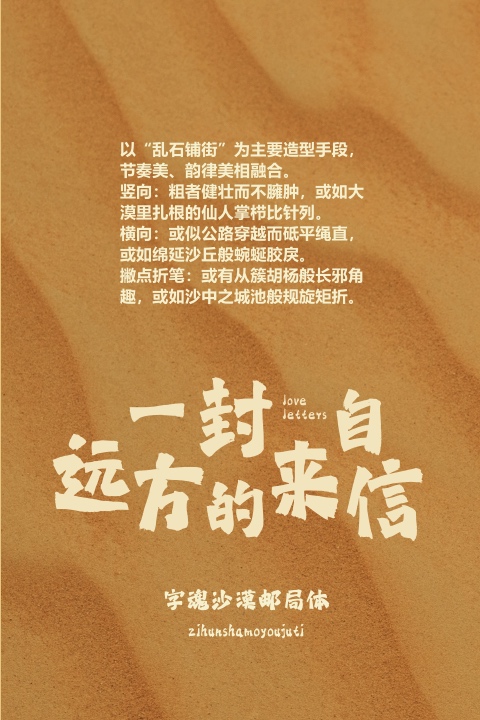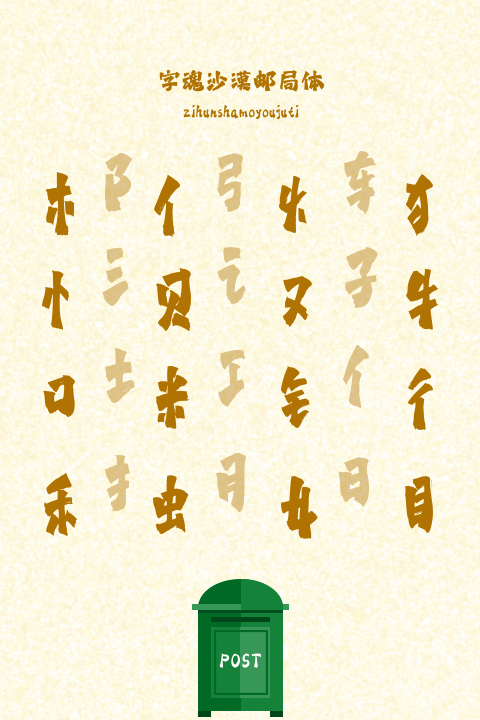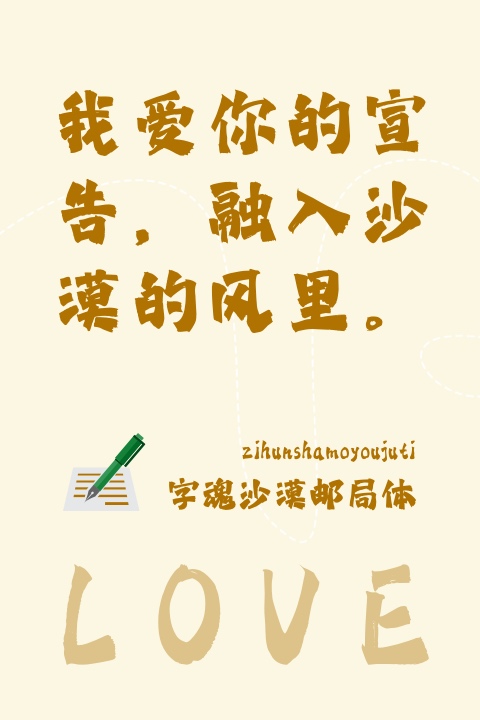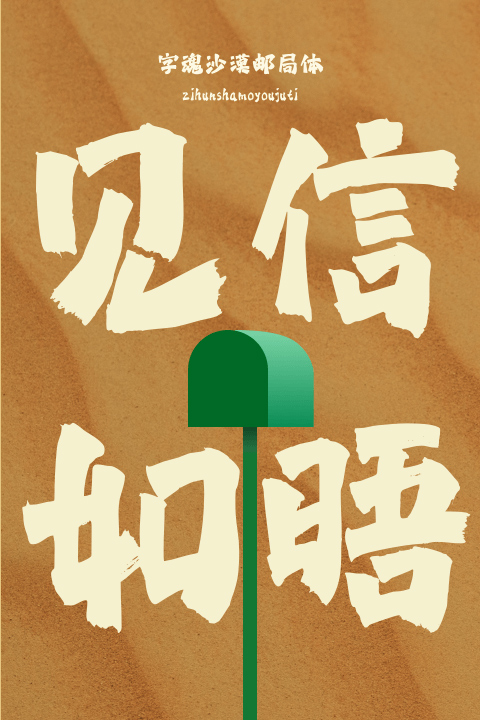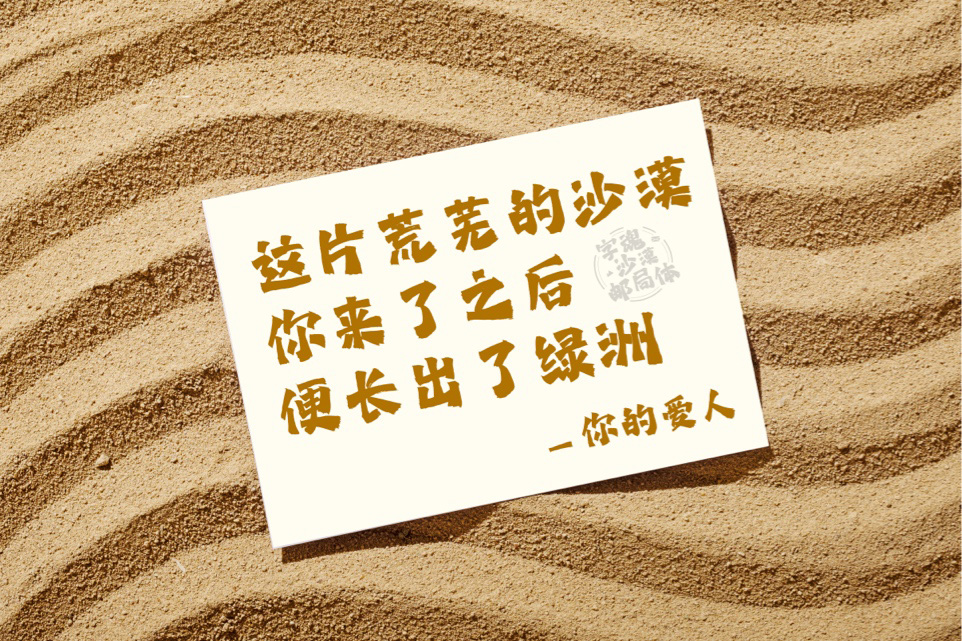
本次,字魂字体来到了中国最“浪漫”的沙漠——腾格里沙漠。这里有着世界上最孤独的邮局——沙漠邮局。2022年间,4000多张爱情明信片从沙漠邮局寄出,穿越千里金色沙海,见证最至性与浪漫的爱情。
2023年5月20日,沙漠邮局携手字魂创意字库,使用字魂x中国邮政沙漠邮局联名字体「字魂沙漠邮局体」,为你书写沙漠情诗。
我们来到了距离邮局10km的穿沙公路,乘坐粉色巴士,开展一场别样的浪漫之旅。公路上用「字魂沙漠邮局体」书写着、向天地大声宣告着你的爱意,为你送来这封世界上最遥远而浪漫的情书。
字体修短相副,异体同势,有沉雄博大的艺术风格。
有浑厚有力,绵里裹铁之意味,以传达沙漠绵延亘古、永恒神秘的意境。